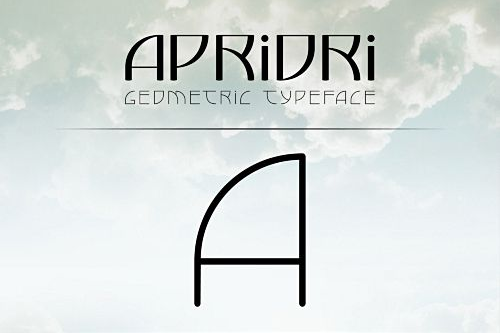
A Apriori é uma fonte desenvolvida por Hamilton que oferece duas estilos principais: leve e regular. Ela traz tanto caracteres latinos quanto círlicos, proporcionando um mix de letras modernas e minimalistas com formas geométricas. Inspirada em modernos tipos de texto minimalísticos e geométricos, a Apriori é uma fonte gratuita para uso pessoal. Para uso comercial, consulte as ligações no final do projeto. Descubra o charme único desta fonte Blackletter.